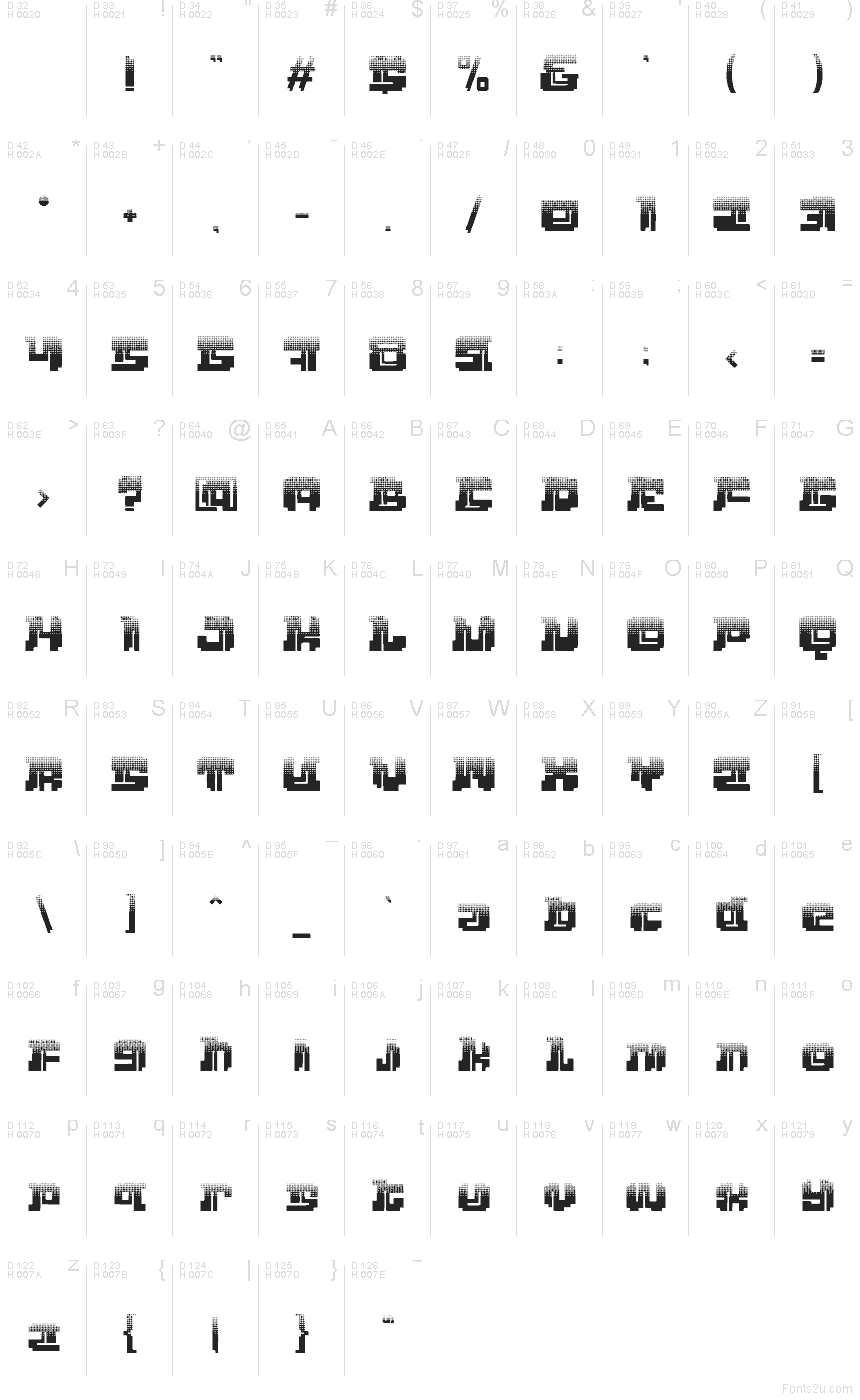
Techno Wave Four od Putracetol Studio je bezplatné futuristické písmo typu display, definované pixelovým rastrem, který přechází do pevných obdélníkových tvarů písmen. Tento posun od tečkovaných vršků k černým základnám dodává písmu rytmus vysílací obrazovky, díky čemuž působí design spíše digitálně než jen geometricky.
Toto písmo je jako stvořené pro herní tituly, sci-fi plakáty, grafiku pro streamování, akční letáky a technické značky, kde krátká slova potřebují syntetický nádech. Protože tečkovaný přechod je součástí struktury, nikoliv jen povrchovým efektem, může také dodat ostrost logům nebo přebalům alb, která vyžadují glitchovou, signálově orientovanou texturu.